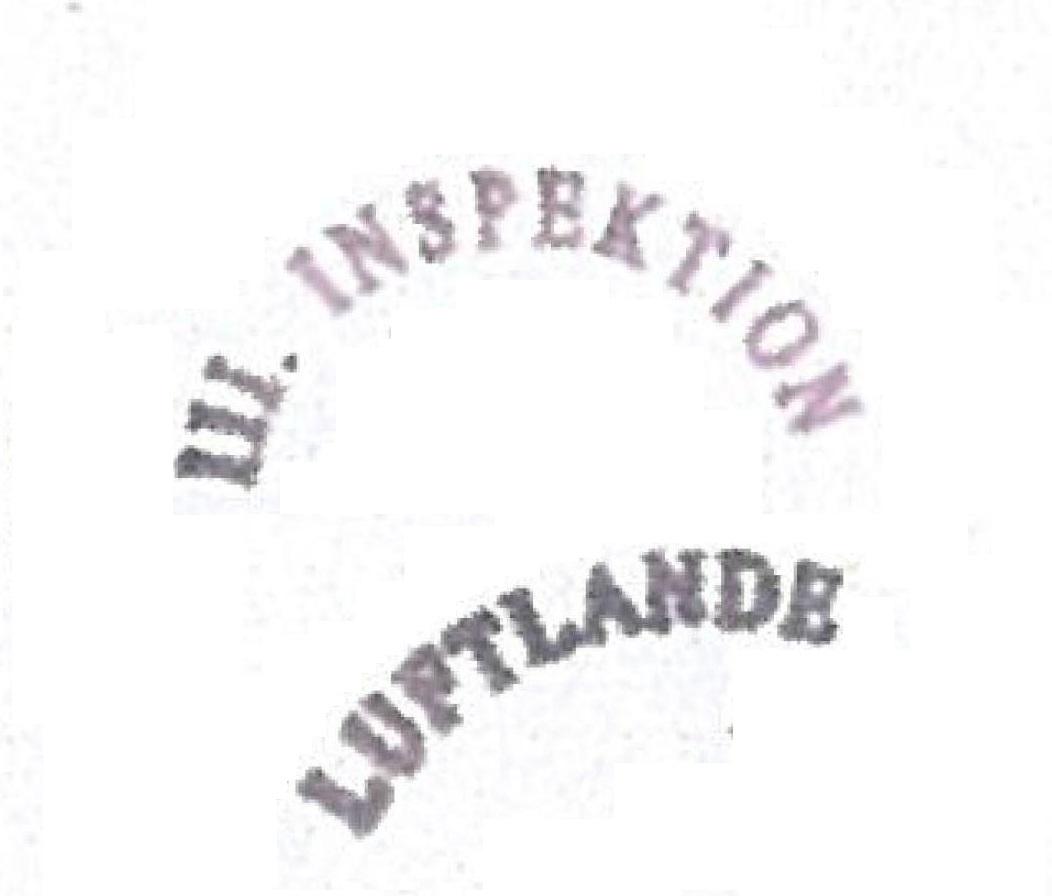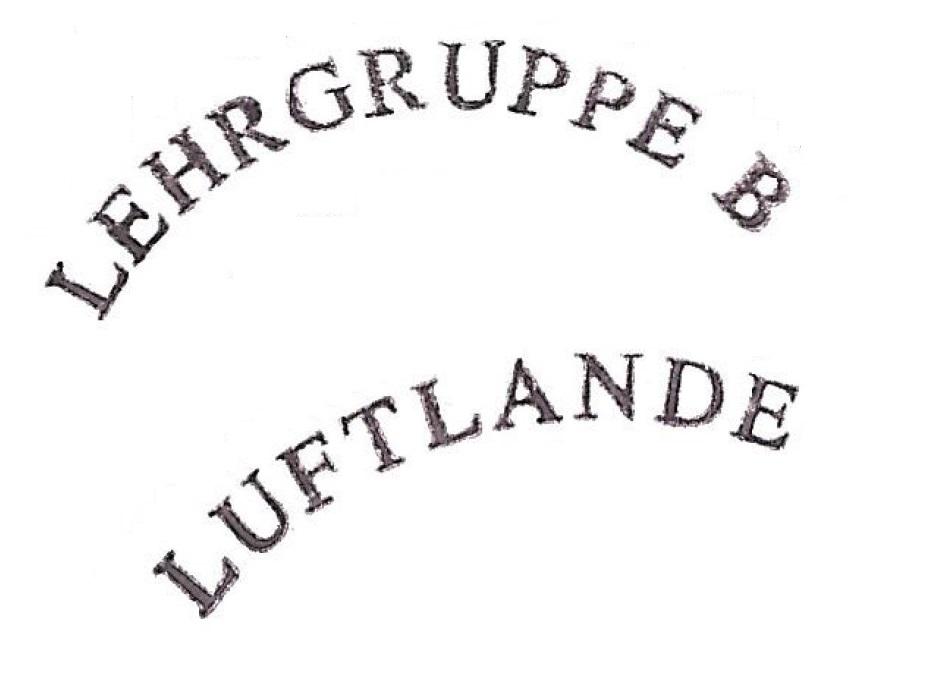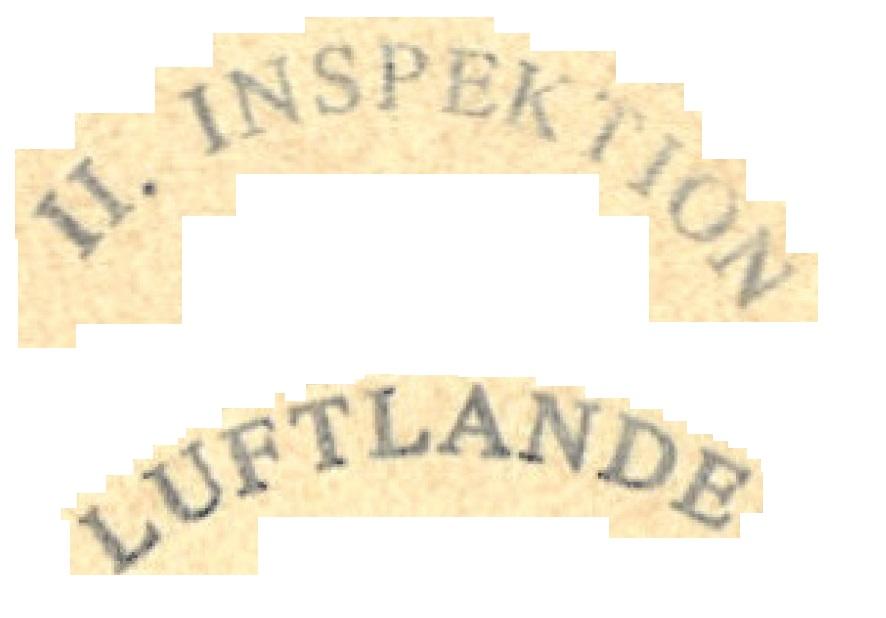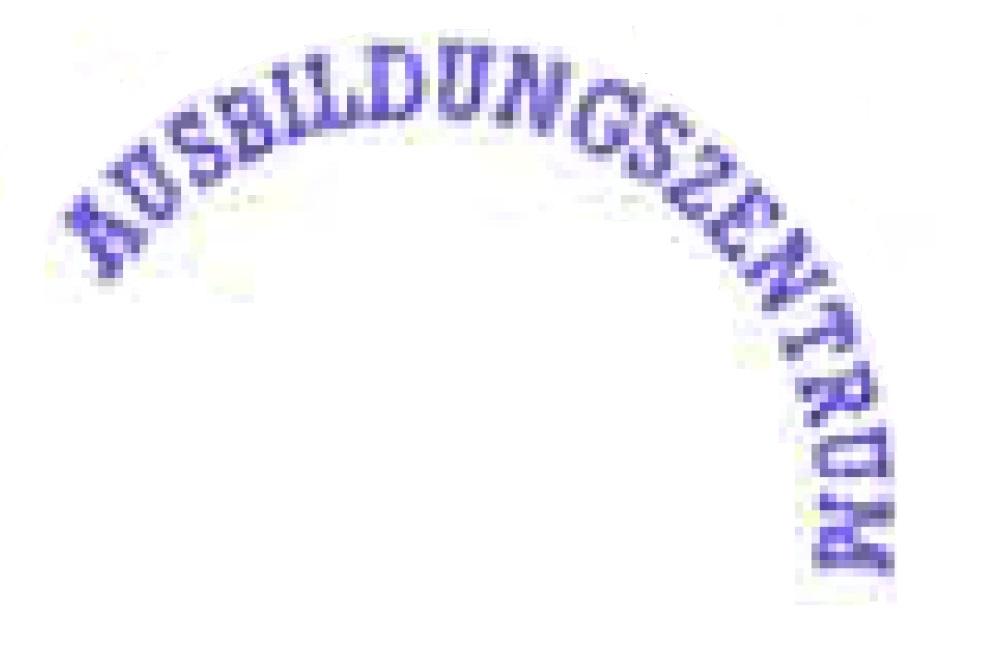
Hallo allerseits, Leute ich suche wieder mal für meine Arbeit für die Wappen solche vier Schriftarten (Schriften) wie unten auf dem Bildern und hoffe, dass Ihr mir damit helfen könnt.
Die Auflösung ist teilweise etwas grenzwertig um richtig helfen zu können.
Ja da haben Sie recht nur leider habe ich keine andere.
Schonmal die Times New Roman für die mittleren vier getestet? Und oben wurde sie wahrscheinlich einfach nur gestaucht oder sogar vorbildlich deren Condensed-Version verwendet.